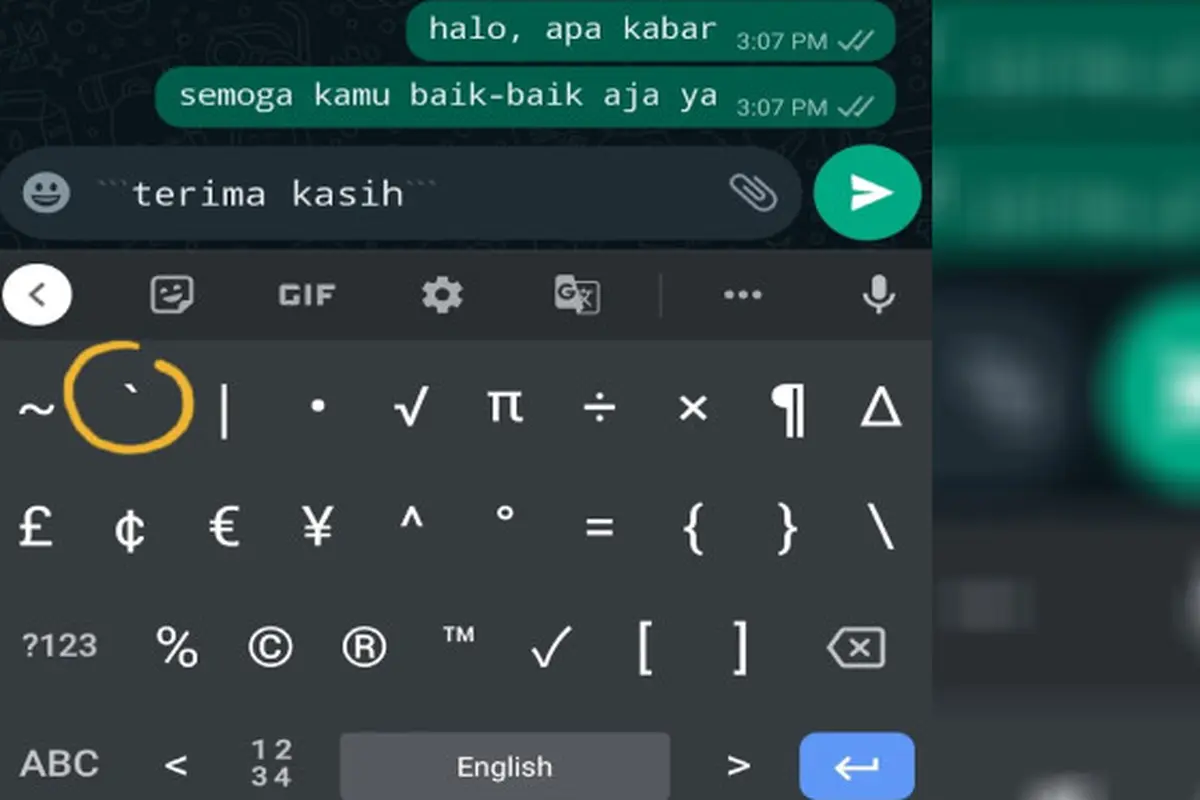
Di sisi lain, sebuah fitur yang tak banyak diketahui di WhatsApp juga memungkinkan kamu untuk mengubah jenis font menjadi terlihat lebih kece, simpel, dan clean.
Kamu juga bisa membuat teks menjadi tebal, miring, atau "mencoret". Caranya terbilang gampang dan kamu bisa langsung melakukannya.
Mengubah Font WhatsApp
Kamu bisa mengubah teks WhatsApp menjadi font monospace. Pertama, kamu harus menemukan ikon backtick, yang terlihat seperti apostrof terbalik.
Di keyboard virtual smartphone, cukup cari tanda baca itu. Kemudian, tempatkan tiga tanda baca tersebut di sebelum dan sesudah pesan, seperti: ```halo, apa kabar?```
Setelah itu, teks pada pesan tersebut akan muncul dengan font monospace.
Mempertebal Teks
Mengutip The Sun, Minggu (16/7/2022), teks tebal (bold) adalah cara yang tepat untuk menekankan kata atau frasa. Itu juga dapat membuat pesan terlihat menonjol, yang berguna dalam obrolan grup.
Yang perlu kamu lakukan adalah menempatkan tanda bintang di kedua sisi kata atau frasa di WhatsApp yang ingin kamu tebalkan, seperti: *halo, apa kabar?*
Itu akan membuat pesan tampak tebal untuk kamu dan semua orang yang melihatnya.
Memiringkan Teks
Kamu bahkan bisa membuat pesan WhatsApp menjadi miring (italic), yang juga sangat bagus untuk penekanan kata atau frasa. Cara kerjanya persis sama dengan trik bold, tetapi menggunakan simbol yang berbeda.
Kamu cuma perlu menempatkan garis bawah di kedua sisi kata atau frasa yang kamu coba edit, seperti: _halo, apa kabar?_
Mencoret Teks
Trik ini biasanya digunakan untuk menandakan bahwa ada sesuatu yang salah, atau harus diabaikan.
Untuk membuat teks dicoret, letakkan tilde (simbol garis berlekuk-lekuk) di kedua sisi pesan kamu, seperti: ~halo, apa kabar?~